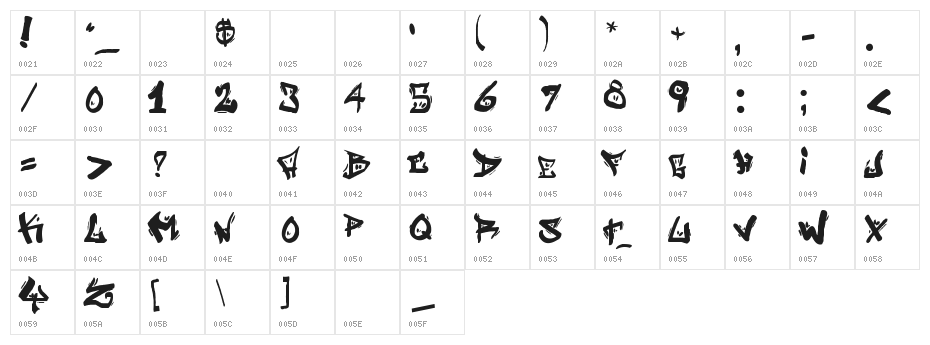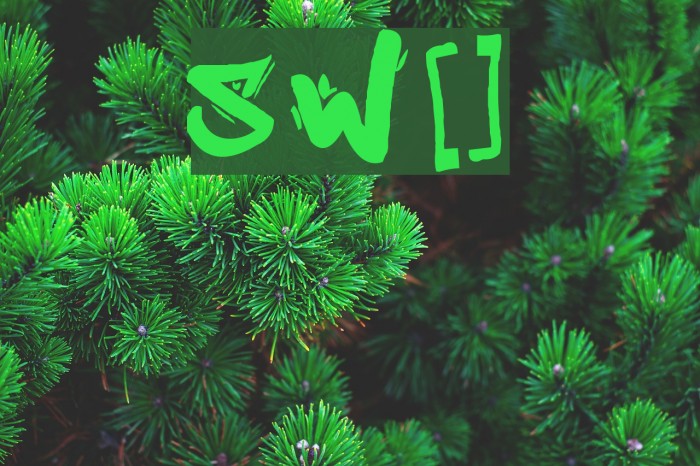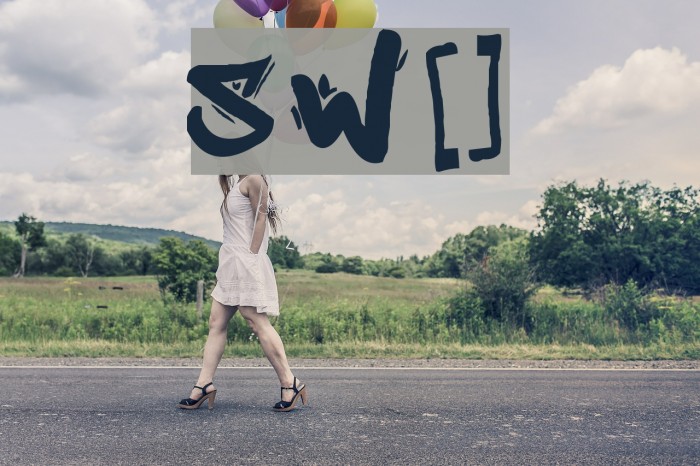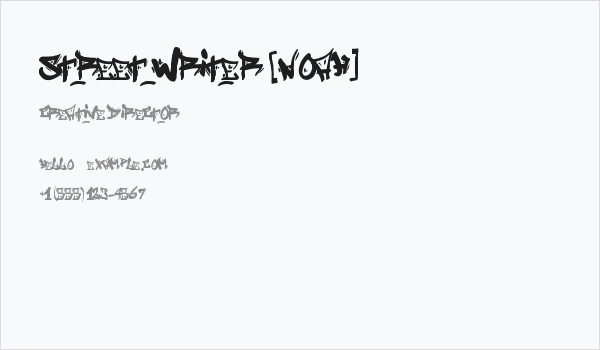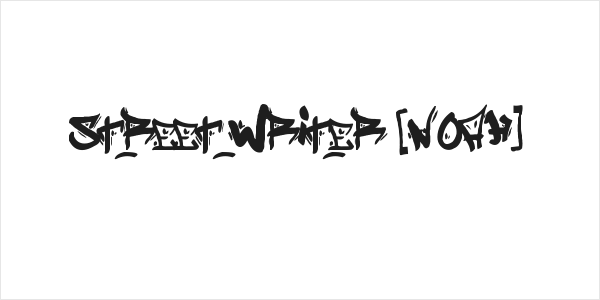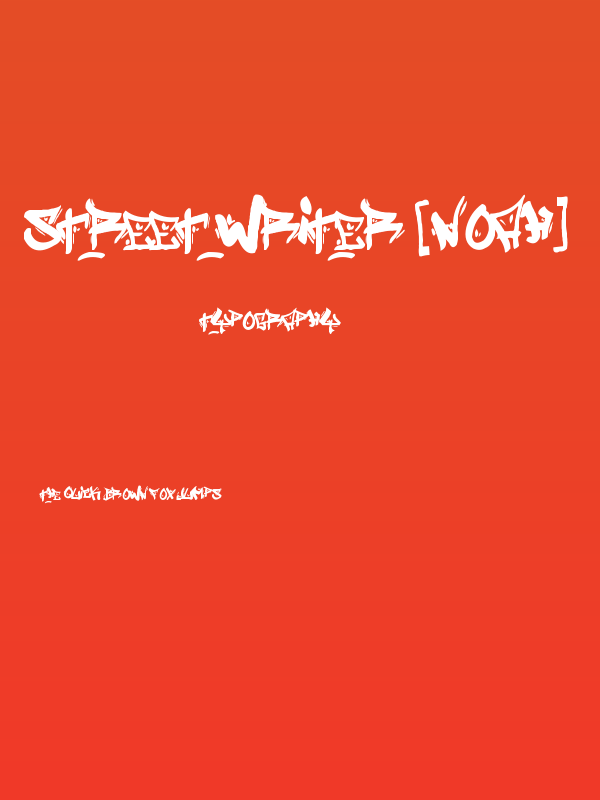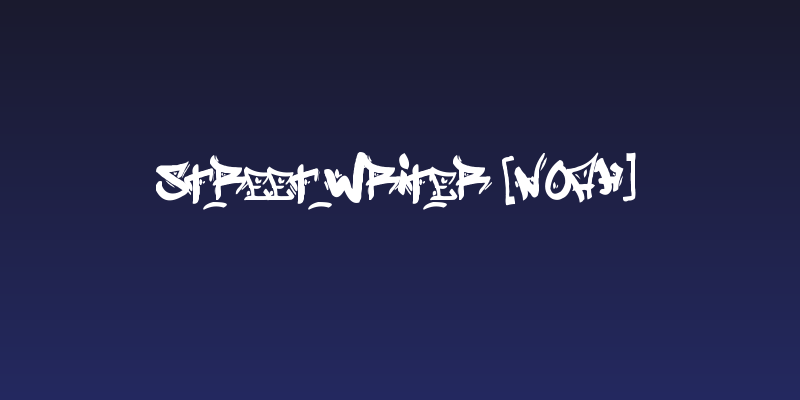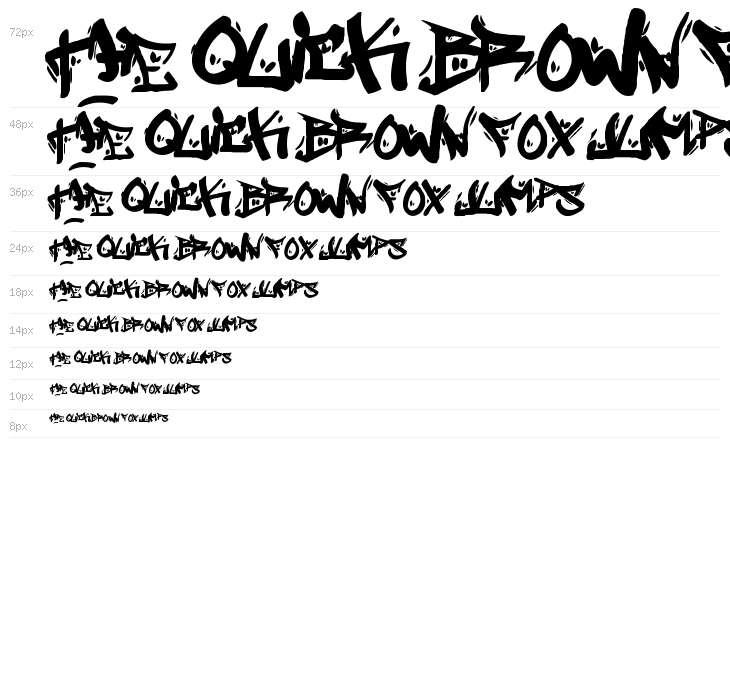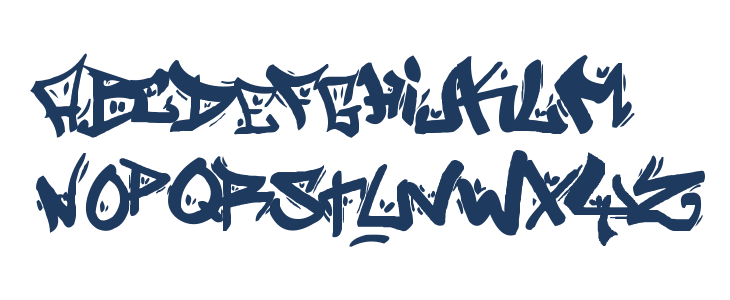
Street Writer [noah] Font
✎ Graffiti
| Stile generale | Urban, Graffiti, Edgy |
| Caso d'uso | Logos, Posters, Headlines |
| Progetti proposti | Perfect for street art designs, urban-themed posters, music album covers, and edgy branding projects. |